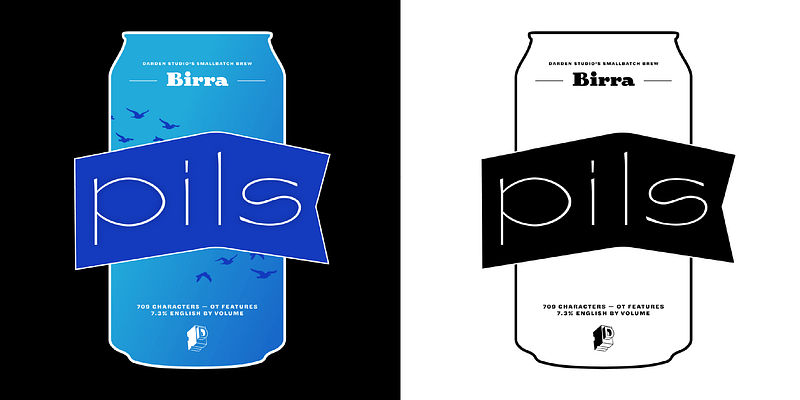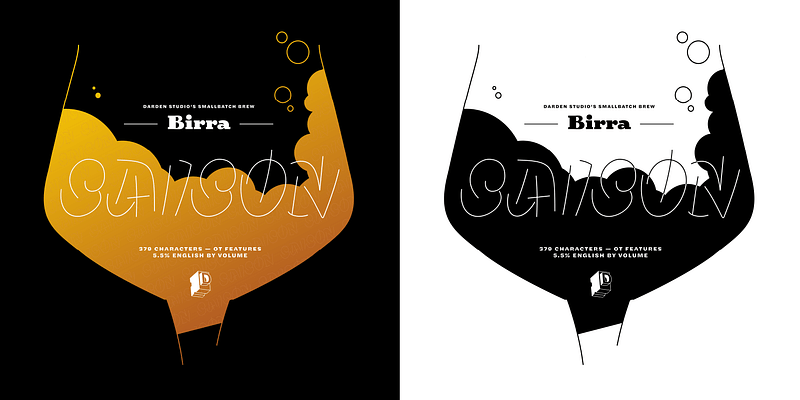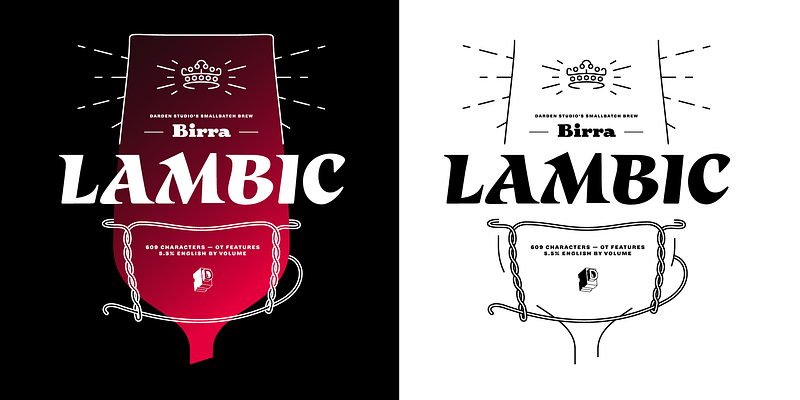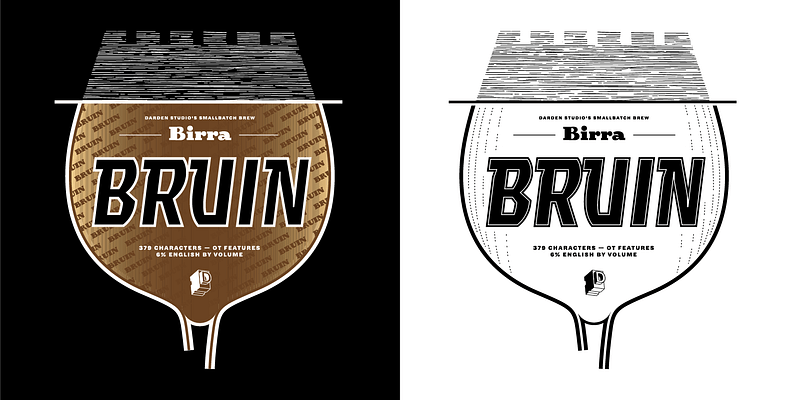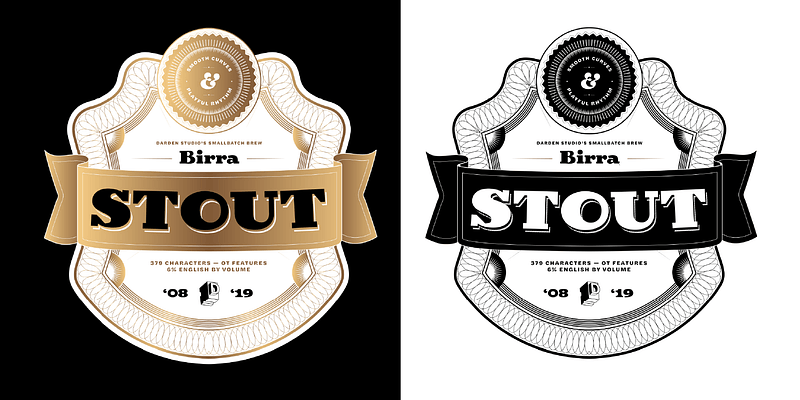
Inspiré des menus de dégustation proposés par les brasseries artisanales d’Amérique du Nord en tant qu’« envol », chaque style est conçu séparément par des designers invités en utilisant un type de bière spécifique comme inspiration. Les types de bière sont disposés de manière à ce que la couleur de la bière corresponde à la graisse du style. Les styles Upright correspondent à des bières au fini sec.
Stout, conçue par Joshua Darden en 2008 comme l’Upright Bold, était la première diffusion d’un projet toujours destiné à évoluer. Résultat d’années de griffonnage compulsif, Stout a été développée avec Matteo Bologna (d’où le nom qui est l’orthographe italienne pour Bière) et publiée pour le distraire.
Bruin, conçue par Elena Schneider en 2019 en tant que Medium Italic, réinterprète les associations familières avec le nom de la bière Oud Bruin (vieille brune) en adaptant le genre de police Blackletter. Elle va bien au-delà du familier en livrant une Blackletter éclatante et contemporaine avec une passion pour les lignes droites. Ajoutant à la richesse de type Bruin, les majuscules et les minuscules n’ont pas exactement la même voix mais créent un joli duo lorsqu’elles chantent ensemble. Les majuscules seules offrent une sensation contrastée.
Saison, conçue par Viktoriya Grabowska en 2020, car Thin Italic ne fonctionne pas, elle joue. Cette « Thin » non traditionnelle primée par le TDC perturbe les classifications de graisse. Vous vous demandez quel style prend plus de place qu’Extra Black et possède des traits aussi légers qu’Hairline ? Saison est rafraîchissante comme le corps nuageux et la mousse imposante de sa bière homonyme. Elle est idéale pour vos pique-niques typographiques les meilleurs et les plus exubérants.
Lambic, conçue par Vera Evstafieva en 2020 est une police qui danse toute la nuit au pub et parvient d’une manière ou d’une autre à arriver à l’heure au travail le lendemain. Il s’agit d’une expérience d’hybridation entre des formes de lettre celtiques et italiques inspirée de l’atelier du calligraphe irlandais Denis Brown. Le résultat est un caractère paneuropéen avec des saveurs d’Irlande, d’Allemagne, de Belgique (et bien d’autres, tous ensemble légèrement inclinés) avec des traces inhérentes d’Europe médiévale.
Birra Pils (Thin) conçue par Mark De Winne a commencé comme une reprise directe de certaines vieilles lettres ornées, que l’on trouve dans un livre spécimen français. Dans sa forme actuelle, elle est distillée de manière significative pour vous donner toute la saveur complexe et juste une touche de vertige. Ses formes osseuses réduisent la gueule de bois tout en gardant beaucoup d’élégance et de saveur, avec des majuscules croustillantes et acidulées, tandis que les minuscules apportent le funk à la maison. Un arrière-goût délicieux se retrouve dans l’assortiment d’émojis pour chatouiller vos papilles typographiques.